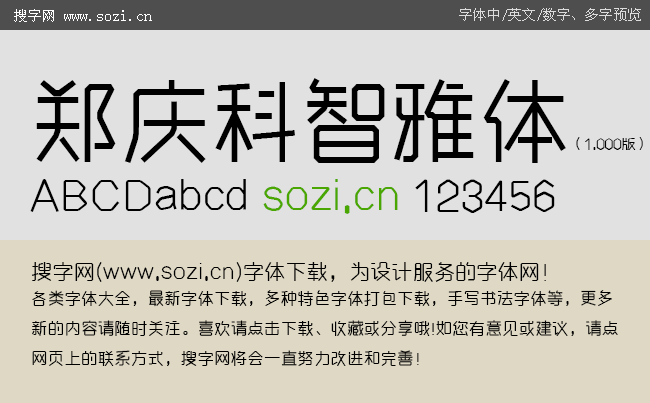
鄭慶科智雅體
搜字網(wǎng)提供一款鄭慶科智雅體中文字體下載,鄭慶科智雅體是一款應(yīng)用于廣告設(shè)計(jì)方面的簡(jiǎn)體中文字體,該字體是基于靜雅體(原時(shí)光體)發(fā)展而來(lái)的一款新風(fēng)格字體,典雅大方,字面松緊適中,轉(zhuǎn)角處的特殊處理是其一大特點(diǎn),筆畫全部采用直線處理,柔美而不失剛毅,適合應(yīng)用于廣告設(shè)計(jì)、名片設(shè)計(jì)、包裝印刷、兒童產(chǎn)品設(shè)計(jì)等應(yīng)用。